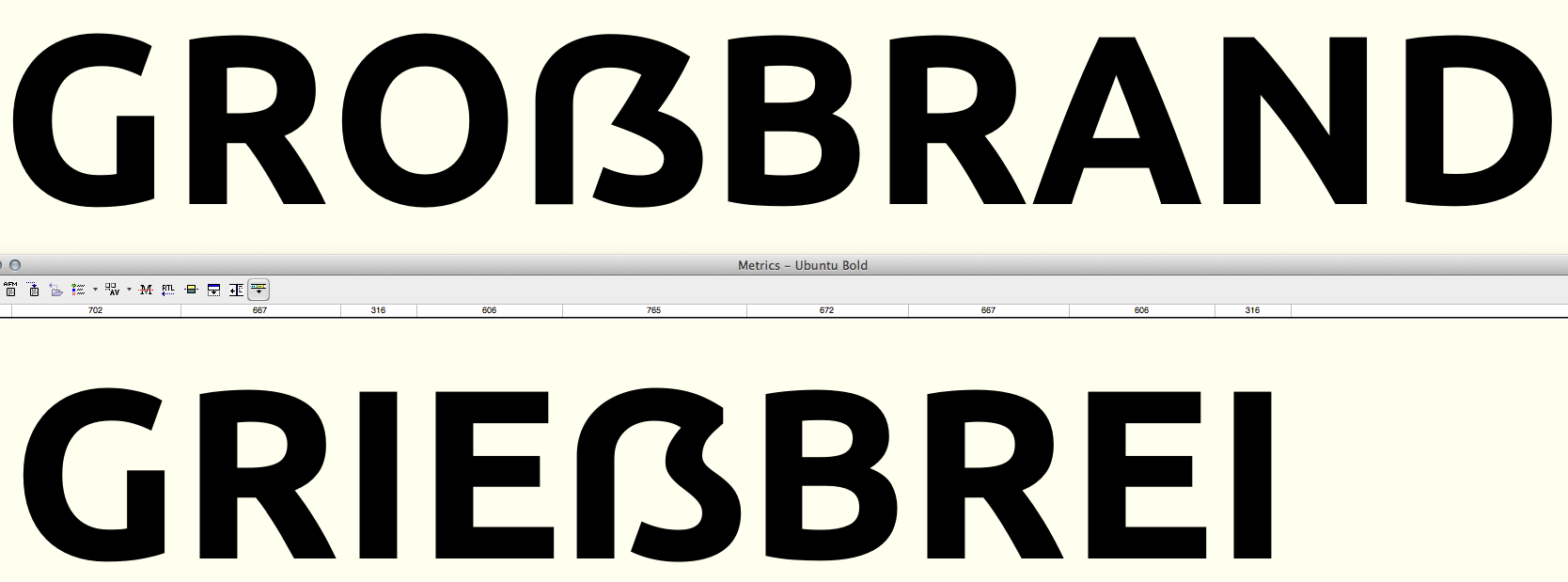
Großes Eszett bei der Ubuntu-Schrift
Wobei die Lizenz der Ubuntu es ja erlauben würde, daraus eine neue Version mit ẞ zu bauen.
Ich habe den Strang da mal überflogen, und sehe, dass der wesentliche Kritikpunkt ja die Sache mit der Form ohne historischen Hintergrund ist, und dass man einfach den Kleinbuchstaben - der aus einer Ligatur aus ſ und s bzw. ſ und z mit Unterschlinge entstanden sei - in die Form eines Versal-Buchstabens hingequält hat.
Vielleicht wäre man dem entgangen, hätte man sich für eine vom Kleinbuchstaben unabhängige Form entschieden, da ja gerade im lateinischen Alphabet sich Gemeine und Versalien ja ohnehin oft unterscheiden, (Aa, Bb, Dd. Ee, Ff, Gg, Hh, Kk, Ll, Mm, Nn, Pp, Qq, Rr, Tt) - wirklich die Mehrzahl schaut anders aus. Da muss ẞ und ß sich nicht unbedingt auch optisch sehr ähneln, und man hätte sich analog zu den Sonderbuchstaben der Isländischen Schrift eben auch in anderen, historisch belegten Schriftsystemen bedienen können. Leider hat uns ein leider recht bekannter Österreicher ja den Weg verbaut, die historisch belegte Form auch dem germanischen Schriftbrauch zu entnehmen und dieses S-Zeichen für das große scharfe S zu nutzen. So bliebe dann ja noch die Wahl, im Kyrillischen oder Griechischen auf Raubzug zu gehen. Mit Σ oder З, oder vielleicht auch Ʒ hätte niemand den Vorwurf machen können, es sei eine nicht historisch belegte Form, noch es sei ja eine eigentlich abzulehnende Ligatur. Auch Ƨ wäre eine Möglichkeit.
Aber egal, Unicode hat das ẞ drin, Tastaturen mit ẞ gibt’s auch schon, warum also nicht hinein, in die Schrift, es wird ja niemand gezwungen, es zu benutzen. Wer’s nicht mag, kann es ja immer noch durch SS ersetzen.
Und was spräche dagegen § zum Buchstaben aufzuwerten, ist das doch auch aus einer SS-Ligatur entstanden, und hinreichend historisch belegt.
Wobei die Lizenz der Ubuntu es ja erlauben würde, daraus eine neue Version mit ẞ zu bauen.
Das Problem hier ist ja nicht, dass Anwender unbedingt eine kosten- und spornlose Groteskschrift mit ẞ benötigen, sondern dass Ubuntu-Systeme in der Default-Konfiguration ein Zwiebelfisch-ẞ anzeigen. Das lässt sich nur lösen, wenn die Ubuntu-Systemschriften um das ẞ erweitert werden.
Stimmt, da hast du recht, und das dann noch dazu, weil man dem Nutzer nichts aufzwingen möchte :hammer:  wobei man ja dann gerade dies macht. indem man den Codepunkt einfach unbelegt lässt, und so eben verfischt wird.
Das wäre doch auch ein schöner Grund, Ubuntu systemweit so aufzubessern, dass alles darauf OpenType voll unterstützt und dann den SS-Fallback als OpenType-Alternative in die Ubuntu-Fonts zu packen. Dann nur noch einen Schalter in die Sprachoptionen, und es wird entweder ẞ oder SS angezeigt, wie es der jeweilige Nutzer am liebsten hätte. Im gespeicherten Text ist dann aber letztlich ẞ enthalten.
Trotz allem habe ich mir mal im mittleren Schnitt ein ẞ gebaut, dass ich hier zur Diskussion stellen möchte:
Cool. Der Ansatz passt doch schon recht gut zur Formensprache der Ubuntu. Aus meiner Sicht wirkt es aber noch zu klein. Daher würde ich den oberen Bogen wie beim R noch etwas ausspannen und nicht gleich abfallen lassen. Vielleicht lässt man den darauf folgenden Diagonalstrich nicht ganz so spitz weiterlaufen und orientiert sich bzgl. Winkel noch stärker am A? Auch der untere Bogen könnte noch ein klein wenig eckiger ausgespannt sein.
Besser, allerdings würde ich den oberen Teil des unteren Bogen (wo er an die Schräge ansetzt) doch nicht ganz so "eckig" nach rechts führen, sondern etwas schneller nach unten fallen lassen – also nicht so sehr am B orientieren sondern doch eher am S.
Und mit der Breite könnte man noch experimentieren – entweder nur den oberen Bogen etwas verlängern und so die Binnenform noch etwas vergrößern und unten öffnen zwecks Unterscheidung zum B, oder aber bewusst das Zeichen wirklich breit machen (mindestens wie das B).
Na, dann stimmt die Breite ja schon :-)
Aber ich habe doch noch einen Hauch hinzugegeben, und den Bogen wieder ein wenig angeschrägt:
Na, dann stimmt die Breite ja schon :-)
Ich sprach natürlich nur vom optischen Eindruck ;-)
Jetzt ist die Breite jedenfalls besser als vorher – Ralfs Beispiele zeigen da nochmal deutlich breitere Formen, hier ist aber die Frage, ob man diese Breiten mit der Ecke links oben optisch schön hinbekommen kann, oder ob man dafür einen runden Bogen braucht um diese Brücke ansprechend zu schlagen.
Bogen unten: finde ich jetzt besser vom Prinzip her – im Feintuning würde ich da jetzt noch 2-4 Stunden rumzupfen ... momentan "sackt" der Bogen für mich jetzt noch nach rechts unten hin ab (vielleicht ist der rechte untere Teil noch einen Tick zu "eckig".
Hab ich den Ubuntu-Bugreport eigentlich richtig verstanden, dass Bruno Maag das Thema jetzt sozusagen "ignoriert"?
Das bedeutet aber nicht notwendigerweise, dass er eine Aufnahme des ẞ in die Ubuntu verhindern könnte. Der letzte Kommentar der Person, in dessen Verantwortungsbereich das ẞ anscheinend fällt, stimmt mich wieder optimistischer:
Persönlich gefallen mir jetzt mal so ganz spontan für die Ubuntu beide Dresdner Formen – sowohl Ralfs als auch deine weiter oben – besser als deine Wolgaster und Ralfs Leipziger. Das kann aber auch daran liegen, dass ich durch die mittlerweile jahrelange Konfrontation mit den Leipziger DejaVu-Zwiebelfischen vorbelastet bin. :-?
Dann biete ich doch mal im Stil der ersten Variante (Dresden-Eckig) die Ausführung für die normale Monospace:
und für die Light: